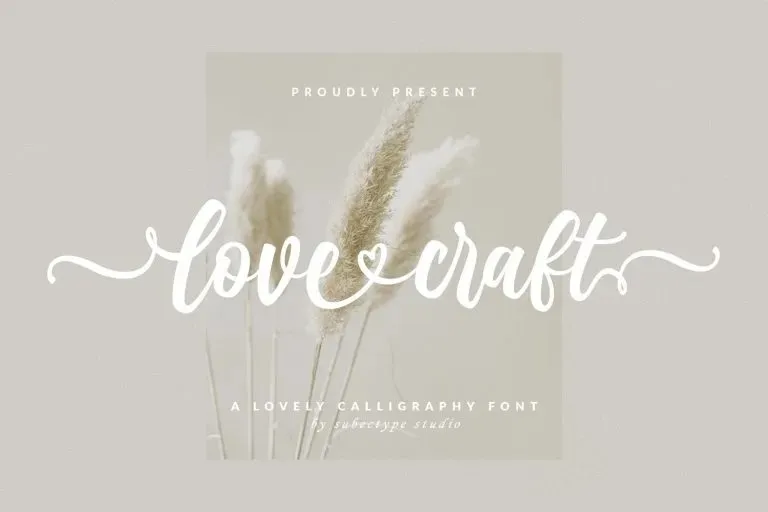
A Love Craft Font é uma elegante fonte cíliar criada pelo designer subetype, com um clima contemporâneo e formas impecáveis inspiradas na chamuscagem clássica de alta qualidade. Esta fonte se destaca por seu estilo único e eterno, perfeita para aqueles que buscam transpor elegância e sofisticação em seus projetos digitais. Perfeito tanto para criações visuais aprimoradas quanto para uma decoração casual, a Love Craft Font é ideal para designers buscando adicionar um toque de profundidade e originalidade às suas ideias. Seja você criando materiais de design editorial ou simplesmente desenhando em seu bloco de notas pessoal, a Love Craft Font está aqui para ajudar a dar vida à sua arte digital.